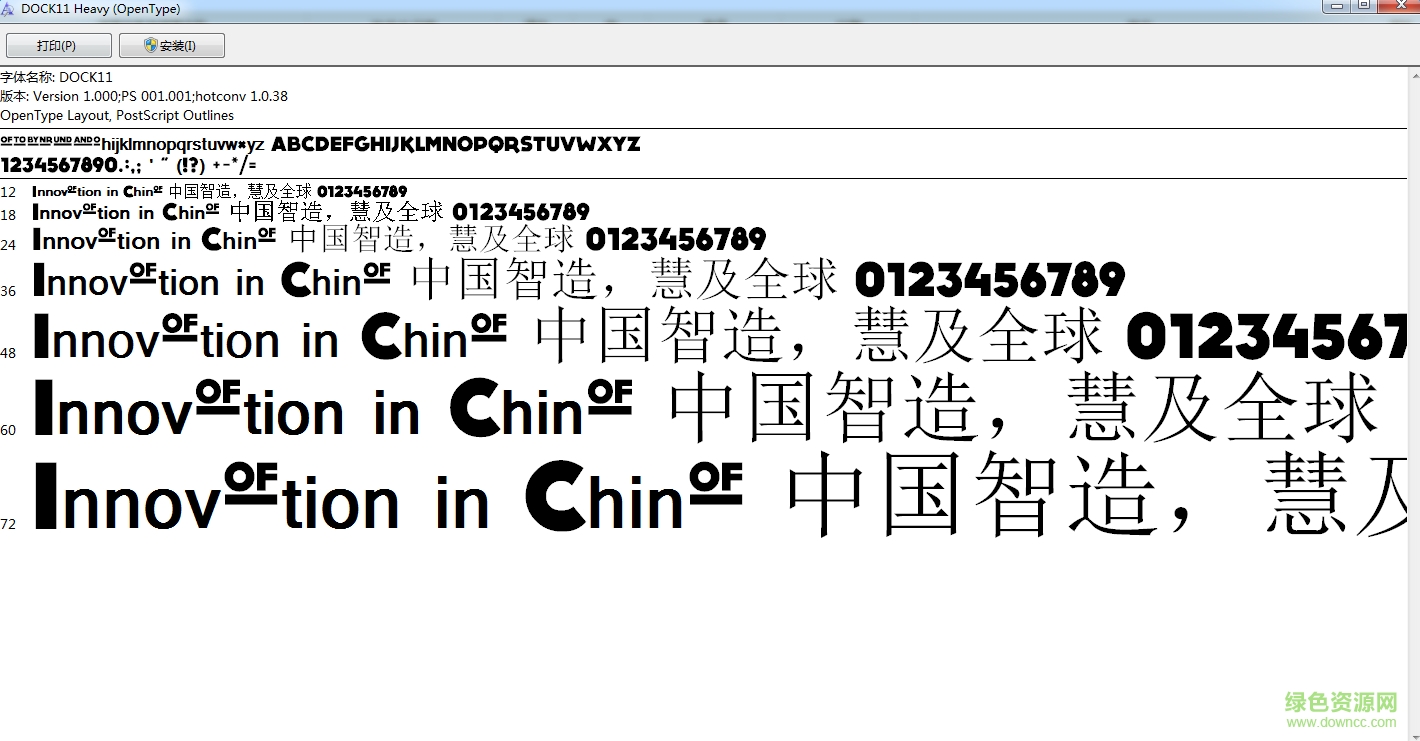
dock11 heavy
dock11 heavy字體是一款獨(dú)特的英文無襯線字體,字符線條粗細(xì)不一,筆畫干練,用在廣告宣傳等領(lǐng)域效果比較好,需要的朋友快來綠色資源網(wǎng)下載吧!
dock11 heavy字體特點(diǎn)
這款字體結(jié)構(gòu)嚴(yán)謹(jǐn),字身緊湊,撇捺舒展,瀟灑美觀,用在很 小的字號時仍具有清晰、明快的閱讀效果!